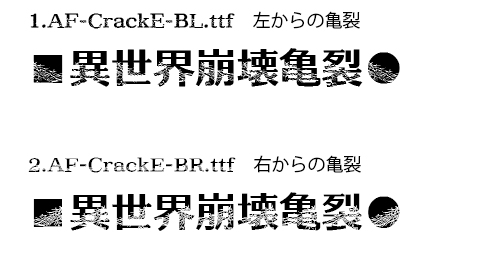
【文字種】
CP932、09 字形
(例えば、辻のしんにょうは1点)
【収録書体】
本商品は下記2書体のセットです。
1)AF-CrackE-BL.ttf 左からの亀裂
2)AF-CrackE-BR.ttf 右からの亀裂
※プレビューフォントは「AF-CrackE-BL.ttf」です。
AF-クラックは太めの明朝体をベースにひび割れた形状で危険を強調する為のデザインフォントです。大見出し、危険の強調、動画テロップやサムネイルへの応用にご検討ください。